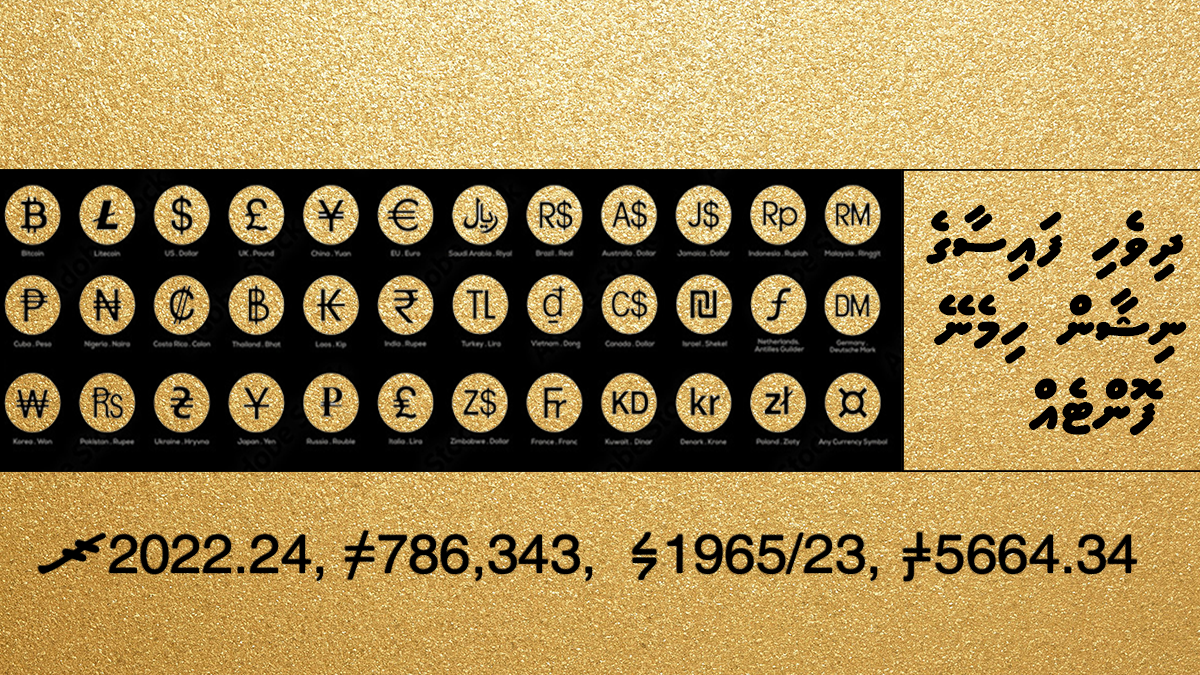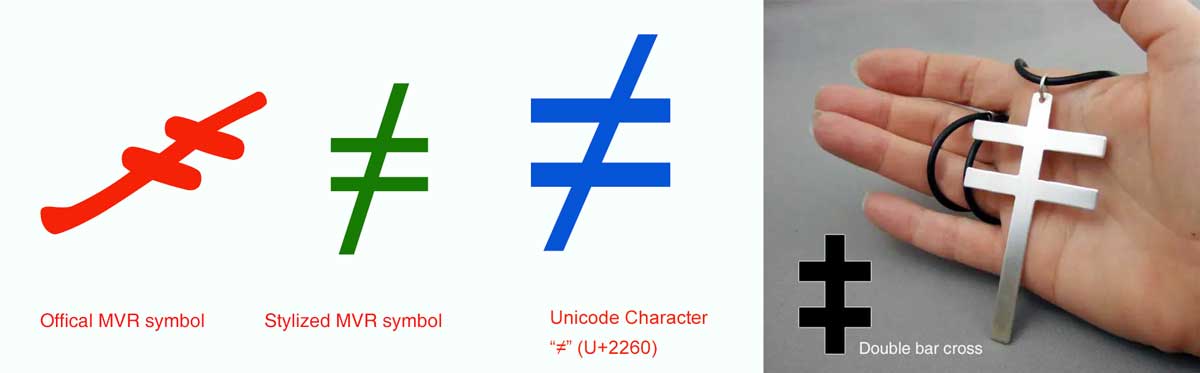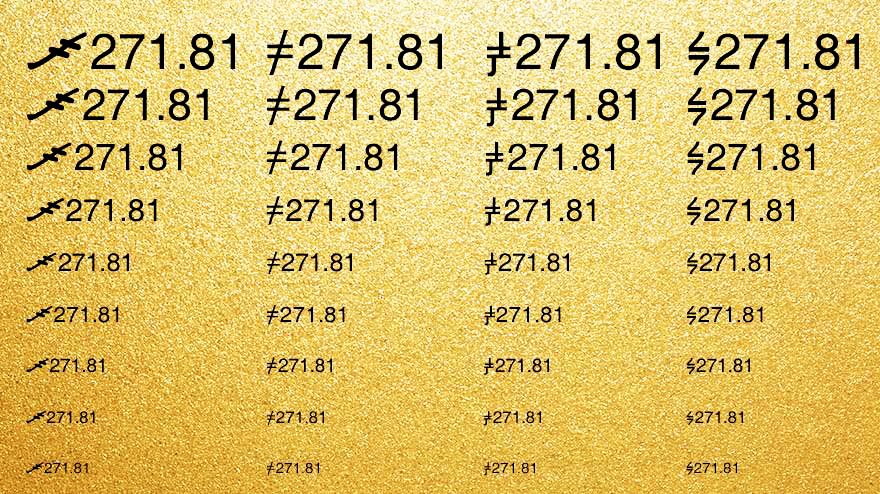
މި މަޒުމޫނުގައި ހިމެނެނީ އަލަށް ފައުޅުކުރެވުނު ދިވެހި ރުފިޔާގެ ރަސްމީ ނިޝާން ހިމެނޭ ފޮންޓަކާއި އެއާ ގުޅޭ މުހިއްމު ވާހަކަތަކެވެ. މި ފޮންޓުން ދިވެހި ފައިސާގެ ނިޝާން ލިޔެވޭނެއެވެ.
ދިވެހި ފައިސާއަށް ދައުލަތުގެ ފަރާތުން ނިޝާނެއް ކަނޑައެޅުމާ ގުޅިގެން، އަޅުގަނޑު މި ފަހަރު މި ހުށަހަޅަނީ އެ ނިޝާން ހިމެނޭ ފޮންޓެކެވެ. މި ފޮންޓުގެ އަޞްލަކީ، ދުނިޔޭގެ އެންމެ މަޝްހޫރު އެއް ފޮންޓު ކަމުގައިވާ ހެލްވެޓިކާ އެވެ. ހެލްވެޓިކާ އަކީ ގިނަ މީހުންނަށް ފެނިފައިވާނޭ ލެޓިން އަކުރުތައް ހިމެނޭ އިނގިރޭސި ފޮންޓެކެވެ. ފޮންޓުގެ އަކުރުތައް ހުންނަ ގޮތް ތިރީގައިވާ ތަސްވީރުން ފާހަގަ ކުރެއްވޭނެއެވެ. އިތުރަށް ދެތުމަށް ބޭނުންވާ ފަރާތްތަކުން މި ޖުމުލައަށް އޮބާލެއްވުމުން އިތުރު މަޢުލޫމާތު ލިބިވަޑައިގަންނަވާނެއެވެ.
ވިންޑޯޒް އިން ގިނަ މީހުންނަށް ފަރިތަ Arial އޭރިއަލް ފޮންޓަކީ ހެލްވެޓިކާގެ ހުތުރު ކޮޕީއެކެވެ. އެމެރިކާގެ ޤާނޫނުތަކުން ފޮންޓަކީ ކޮޕީރައިޓް ކުރެވޭ އެއްޗެކެވެ. ނަމަވެސް، އަކުރުތަކުގެ ބައްޓަންތަކެއް ނުވަތަ ޓައިޕްފޭސް އެއް (typeface) ކޮޕީރައިޓް އެއް ނުކުރެވެއެވެ. އެހެންކަމުން، އެކި މީހުން އެކި ފޮންޓުގެ އަކުރުތަކުގެ ބައްޓަންތަކާ އެއްގޮތަށް އެހެން ފޮންޓުތައް ހަދައި، ފާޅުކޮށް ފަތުރައި ހަދަތެވެ.
ޢާއްމު ގޮތެއްގައި ދިވެހި ރުފިޔާގެ ނިޝާން ބޭނުންކުރާނީ ހިސާބު ނަންބަރުތަކާ ޖެހިގެންނެވެ. އެއީ އެހެން ފައިސާގެ ނިޝާންތައް ވެސް އެންމެ ގިނައިން ބޭނުންކުރާ ގޮތް މެއެވެ. އެހެންކަމުން، ދިވެހި ރުފިޔާގެ ނިޝާން ހިމަނާފައިވާ ފޮންޓްގައި ތާނަ އަކުރުތަކެއް ނުހިމަނަމެވެ. ދިވެހި ބަހާއި އިނގިރޭސި ބަސް ލިޔެވޭގޮތަށް ހުންނަ ކޮމްޕިއުޓަރުތަކުން، މި ފޮންޓުން ދިވެހި ފައިސާގެ ނިޝާން ޖެހުމަށް ބޭނުންކުރަންވާނީ އިނގިރޭސި ކީބޯޑެވެ.
މި ފޮންޓު ފައުޅުކުރުމުގެ ބޭނުމަކީ އައު ނިޝާނާ އެކު އެއްޗެއް ލިޔަން ބޭނުންވާ މީހުންނަށް އެ ފުރުސަތު ދިނުމެވެ. މިސާލެއްގެ ގޮތުން ވިއްކާ މުދަލުގައި އަގުޖެހުން ފަދަ ކަންކަން ކުރުމެވެ. ފޮންޓަށް ކިޔާފައިވާ ނަމަކީ MV Currency Symbol އެވެ. ދެން ތިކުރައްވާ ސުވާލަކީ، ފިތާނީ ކީބޯޑުގެ ކޮން ފިތަކަށް އެހެން ނޫންތޯއެވެ؟ އާދެ! ދިވެހި ރުފިޔާގެ ނިޝާން އަޅުގަނޑު ހިމެނީ ވަރަށް މަދުން ބޭނުންކުރާ ފިތެއް ކަމުގައިވާ ` މި ނިޝާން ހިމެނޭ ފިތުގައެވެ. މި ފިތަކީ ކީބޯޑުގެ 1 ގެ ވާތް ފަރާތުގައިވާ ފިތެވެ. މި ފިތަށް ފިތާލުމުން ފައިސާގެ ރަސްމީ ނިޝާން ޖެހޭނެއެވެ. ދެން އެއަށް ފަހު، ފައިސާގެ މިންވަރު (ވިޔަ ޢަދަދުތައް) ޖަހާނީއެވެ.
ޝިފްޓް އޮބައި ހިފަހައްޓައި ފައިސާގެ ނިޝާންޖެހޭ ފިތަށް އޮބުމުން، ޖެހޭނީ ރުފިޔާގެ ރަސްމީ ނިޝާން ސްޓައިލައިޒް ކޮށްފައިވާ ނިޝާނެކެވެ. ސްޓައިލައިޒް ކުރުމަކީ އެއްޗެއްގެ އަޞްލު އޮންނަ ގޮތަށް ކުޑަ ބަދަލެއް ގެނެސް، އެހެން ފޭޑިއެއް އޭގައި ޖެއްސުމެވެ. މިސާލެއްގެ ގޮތުން، ފައިސާގެ ނިޝާން އަޞްލު އޮންނަގޮތަށް ކުޑަ ބަދަލެއް ގެނެސް، ވިޔަ އަކުރުތަކާ ލާމެހި ގުޅޭ ގޮތް ހެދުމެވެ. ހާމަނައިޒް ކުރުމެވެ. މިހެން ހަދައިފިނަމަ މި ނިޝާން އޮންނާނީ ≠ މި ފަދަ ގޮތަކަށެވެ.
ހިސާބު އެނގިވަޑައިގަންނަވާ ބޭފުޅުންނަށް މިއީ ކޮން ރަމްޒެއްކަން އެނގިވަޑައި ގަންނަވާނެއެވެ. އާދެ! އެއީ ޢަދަދެއް އެއްވަރު ނޫންކަމަށް ބޭނުންކުރާ ނިޝާނެވެ. ( ”≠“ not equal to) ގެ ނިޝާނެވެ. ފައިސާގެ ޢަދަދުތަކެއްގެ ކުރީގައި ޖަހަން ވަރަށް ”ބިރުބޮޑު“ ނިޝާނެކެވެ. މި ނިޝާން ތެދުކޮށްފިނަމަ، ދެން ޖެހޭނީ ޑަބްލް ބާރ ކްރޮސް އެވެ. މިއީ އިރުމަތީ ޔޫރަޕުގެ ނަޞާރާއިންގެ ނިޝާނެކެވެ. މި ދެ ނިޝާނަކީ ނާދިރު (ޔުނީކް) ނިޝާނެއް ނޫނެވެ. ޔުނިކޯޑްގައި މި ދެ ނިޝާން ވެސް ހިމެނެއެވެ. ތާނަ ފޮންޓްތައް ފަރުމާކުރާއިރު، ވަރަށް ފަސޭހައިން ރ ގައި ޞަލީބެއްގެ ސިފަ ޖެހެން އުޅެއެވެ. އެހެންކަމުން، ރ ގެ ބައްޓަން ކާލިގަނޑަކާ ވައްތަރު ވިޔަ ނުދޭން އަޅުގަނޑުގެ ވިސްނުން މި ޖުމުލައަށް ފިތާލުމުން ފެނިވަޑައިގަންނަވާ ފޮންޓުތަކުން ފާހަގަ ކުރެއްވޭނެއެވެ.
މި ފޮންޓުގައި ދިވެހި ރުފިޔާއަށް އަޅުގަނޑު ފަރުމާކޮށްފައިވާ ދެ ނިޝާނެއް ވެސް ހިމެނެއެވެ. އެ ނިޝާންތައް ވަނީ [އެންޓަރ – Enter] އާ ގާތުގައިވާ | \ މި ދެ ނިޝާން ހިމެނޭ ފިތުގައެވެ. އަޅުގަނޑު ބޮޑަށް ތާއީދުކުރާ ނިޝާންވަނީ \ ގައެވެ. | ގެ ބަދަލުގައިވަނީ އެހެން ނިޝާނެކެވެ. މި ނިޝާނުގެ މައްސަލައަކީ، އެ ނިޝާން ކެމިސްޓްރީގައި ބޭނުންކުރާ ⇌ ރިވާސިބްލް reversible (އިކްވިލިބްރިއަމް) ނިޝާން އާ ވައްތަރު ގޮތެއް ހުރުމާއި، ރ އާ އެހާ ވައްތަރު ނުވުމެވެ.
ތިރީގައި އެވަނީ އެކި ސައިޒުގެ އަކުރުން މި ދެންނެވުނު ހަތަރު ނިޝާނާ އެކު ވިޔަ ޢަދަދު ތަކެއް ލިޔެފައެވެ. ތިބާއަށް ރީތީ ކޮށް ނިޝާނެއް ތޯއެވެ؟
ރީތި ހުތުރަކީ އެކި މީހުންނަށް ތަފާތުވާ ސިފައެކެވެ. ދައުލަތުގެ ފަރާތުން ވަކި ނިޝާނެއް ރުފިޔާއަށް ކަނޑައެޅުމުން، ގްރެފިކް ނިޒައިނަރުން އެއަށް ކުދިކުދި ބަދަލުތައް ގެނެސް ޒަމާންތަކުގެ ދައުރުވުމުން އެއަށް ތަފާތު ބަދަލުތައް ގެނުވައެވެ. މިސާލެއްގެ ގޮތުން، އިހުގައި ތާނަ އަކުރުތަކާއި މިހާރު ތާނަ ލިޔާ އަކުރުތައް ވަރަށް ތަފާތެވެ. ބައެއް ތަކެތި ލޮލަށް ގިނައިން ފެންނަން ފެށުމުން އެއްގޯސްވެ ރީތިވާގޮތް ވެސް ވެއެވެ. ދިވެހި ފައިސާގެ ނިޝާނަށްވެސް ވާނީ މިހެންނެވެ. އެއްވެސް ކަމެއް، އެއްވެސް އެއްޗެއް އަބަދަކު އެއްގޮތަކަށް ނުހުރެއެވެ.